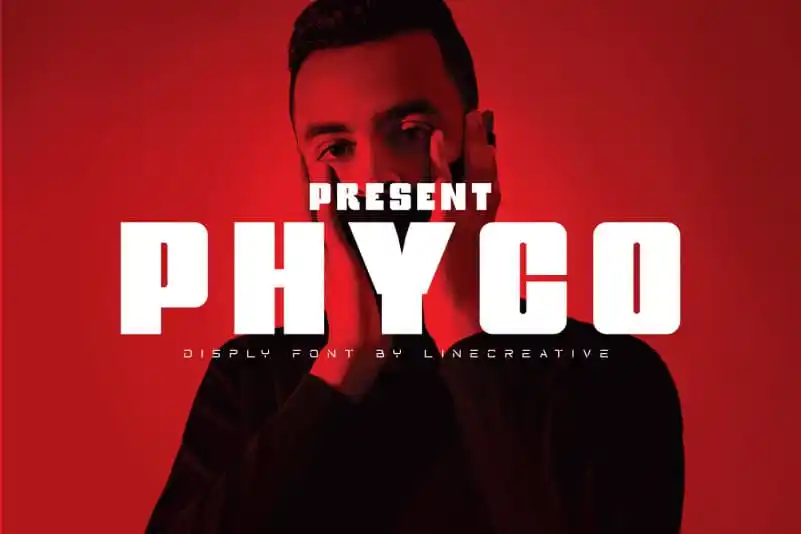
A Phyco Display Font é uma fonte sans-serif que se destaca pela sua simplicidade elegante e facilidade na criação de textos profissionais ou criativos. Seu design limpo e minimalista permite que qualquer tipo de texto seja apresentado com clareza, seja em logotipos modernos até em peças de design editorial de revistas. O designer ari trouxe uma característica única para essa fonte – seu estilo clean é complementado por linhas levemente curvadas e arruelas finas que dão ao texto um toque versátil sem perder o aspecto moderno. Esta fonte não apenas se destaca como uma opção de tipo eficiente, mas também traz vida à sua marca ou projeto de design. Para quem deseja adquirir a Phyco Display Font e acessa-a em ambientes comerciais, a aritjuanda.com é um lugar sólido para o fazer.